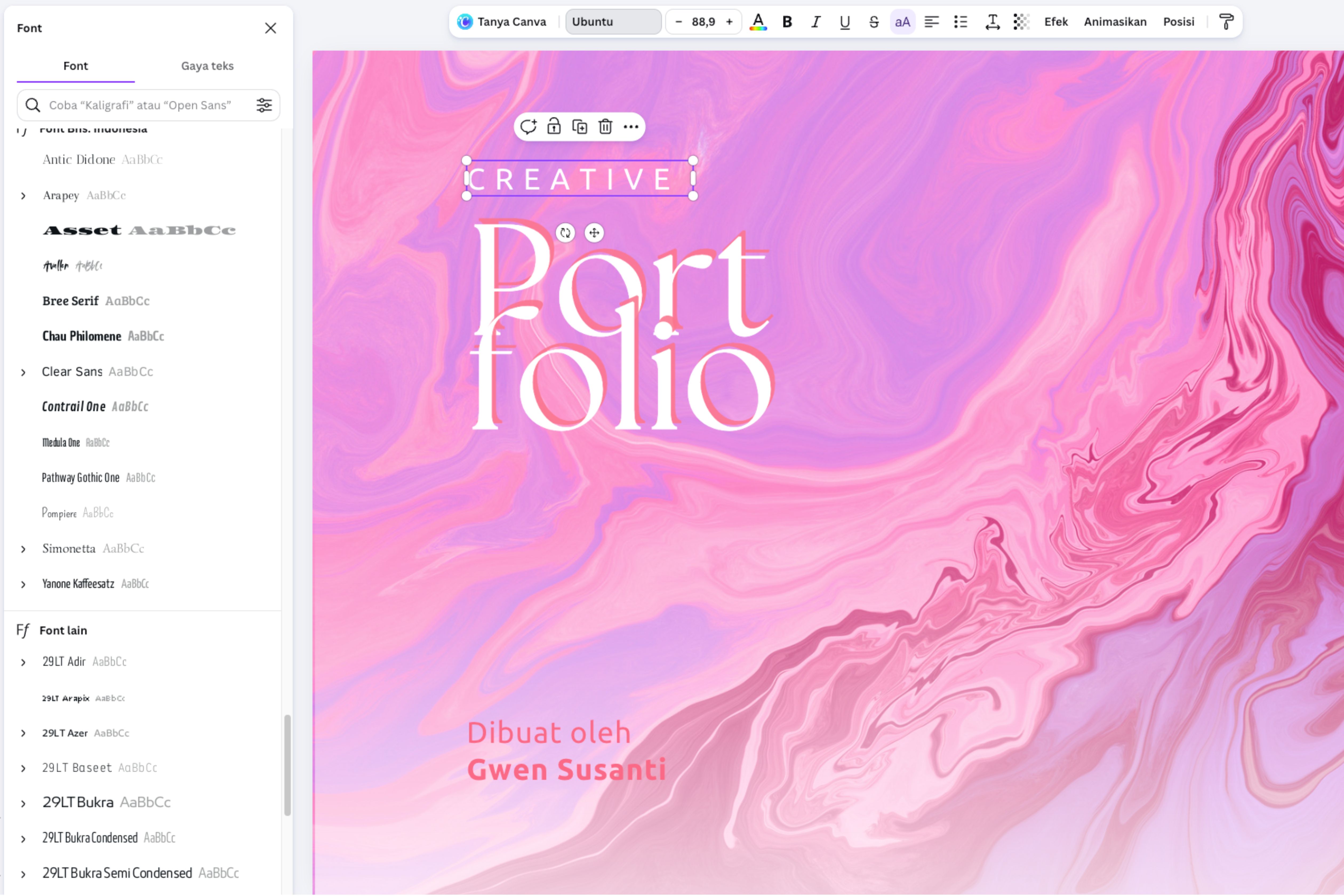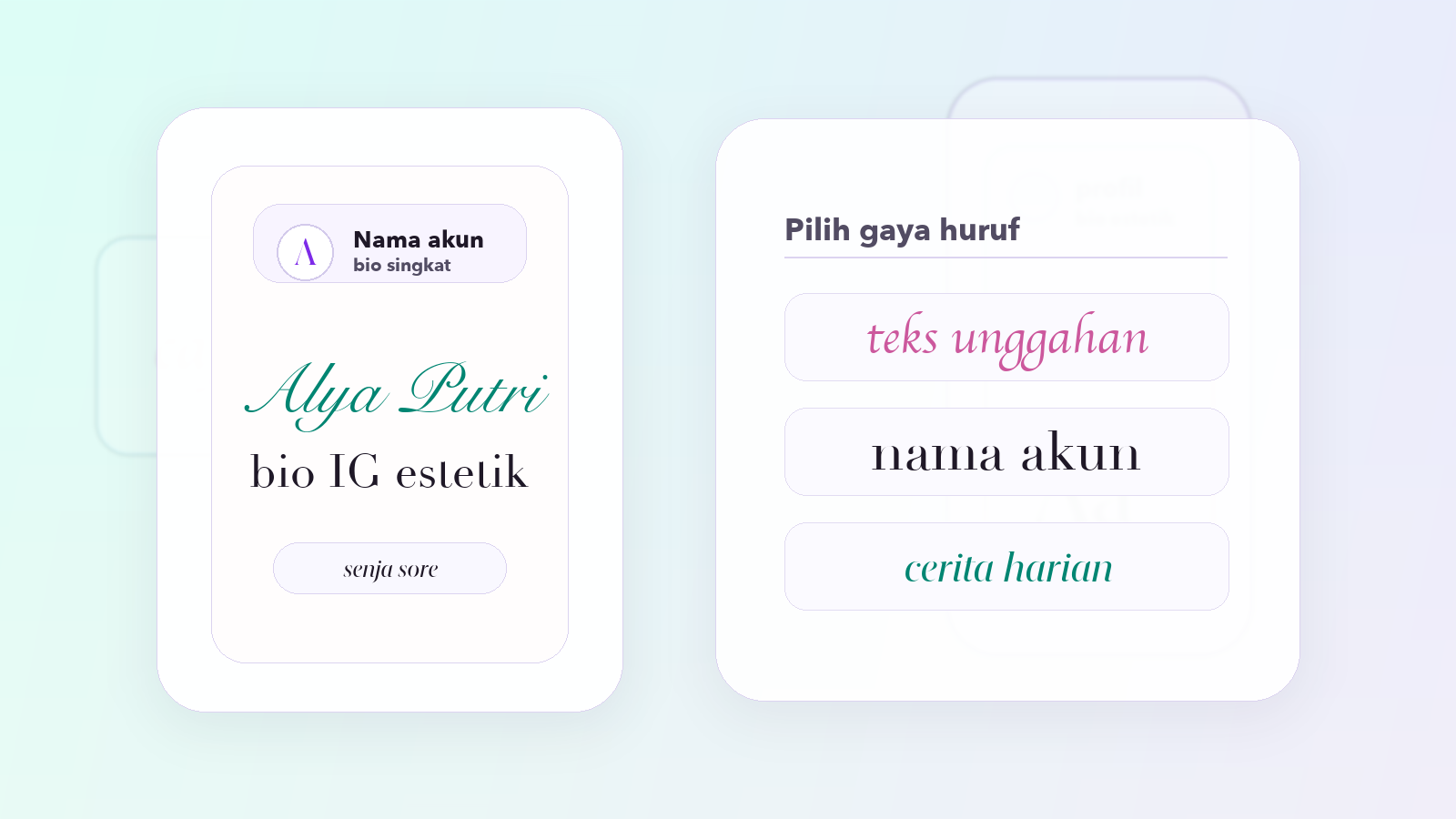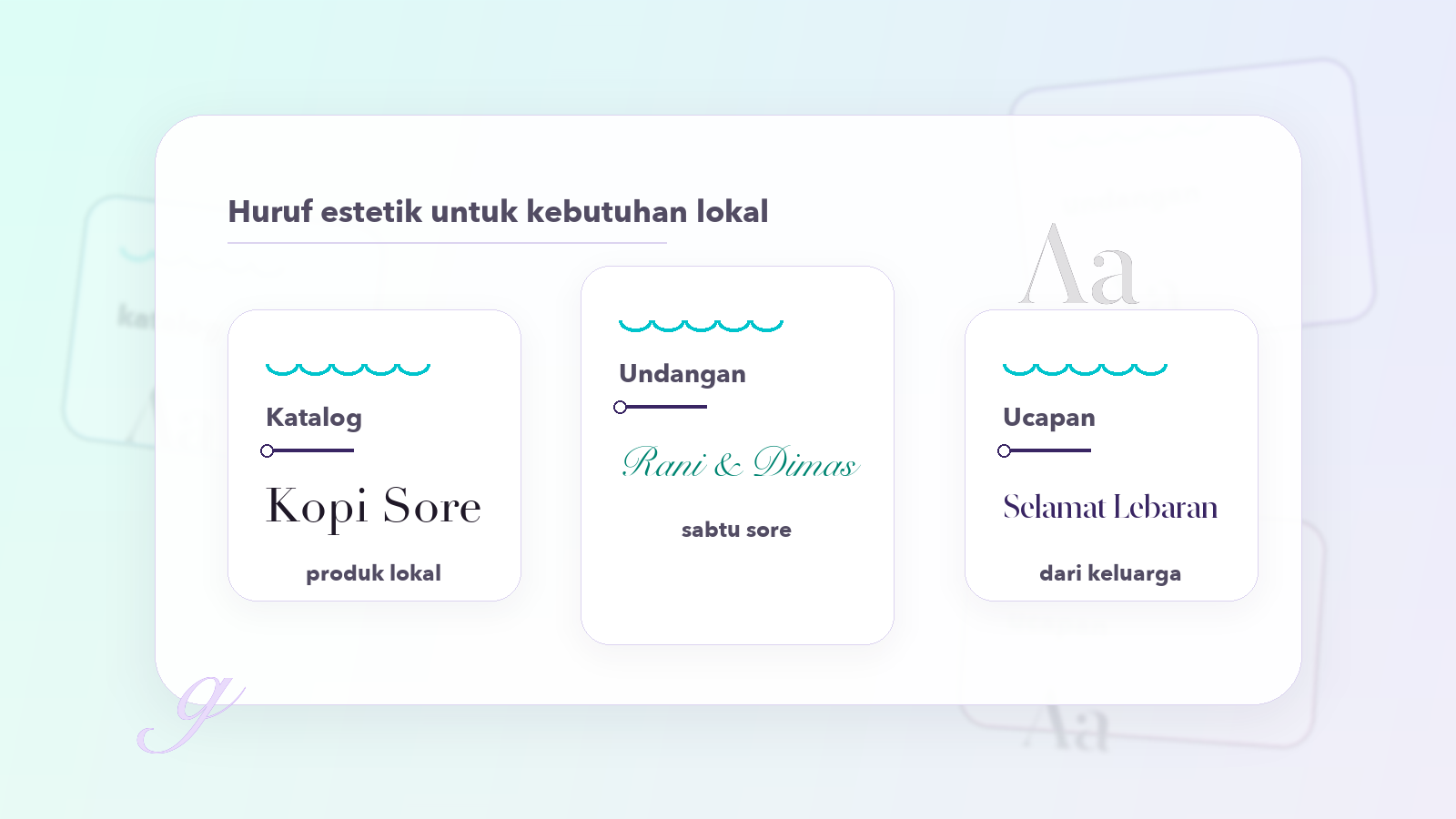
font aesthetic
Font aesthetic gratis untuk tulisan aesthetic
Pilih ratusan huruf aesthetic siap pakai di Canva untuk bio Instagram, nama akun, caption, dan judul. Ketik teks Anda, terapkan font aesthetic favorit, lalu unduh sebagai gambar, tanpa keahlian desain.
Ratusan huruf aesthetic gratis, langsung pakai
Canva menyimpan ratusan huruf aesthetic yang bisa Anda pakai gratis. Jenis font aesthetic-nya lengkap, mulai dari serif elegan, sans-serif modern, tulisan tangan, hingga display dekoratif.
Beberapa nama font aesthetic populer adalah Canva Sans yang bersih, Glacial Indifference yang minimalis, dan Playfair Display yang mewah. Cukup sorot teks, buka daftar font, lalu telusuri semua pilihan langsung di editor tanpa perlu mengunduh apa pun.
Perpaduan huruf aesthetic dan AI
Setelah teks dan visualnya siap, tinggal terapkan font pilihan Anda agar tampilan makin selaras. Perpaduan alat AI dan huruf estetik ini memangkas waktu dari ide sampai desain jadi.
Teks yang bisa diedit dan dipadukan
Berbeda dari gambar teks yang kaku, setiap font estetik di Canva menempel pada teks asli yang bisa Anda ubah kapan saja, termasuk lewat aplikasi Canva di iPhone dan Android.
Ganti kata, ukuran, warna, dan spasi hanya dengan beberapa klik, atau berganti font tanpa mengetik ulang. Untuk hasil terbaik, padukan satu font berkarakter untuk judul dengan satu font sederhana untuk isi, lalu simpan kombinasinya ke Kit Merek⁠(terbuka di tab atau jendela baru) agar konsisten di semua desain.
Font IG aesthetic untuk bio, caption, dan feed
Font Instagram aesthetic membuat bio, caption, dan feeds IG⁠(terbuka di tab atau jendela baru) terlihat menonjol. Pilih font IG aesthetic yang tipis atau bergaya tulisan tangan untuk kesan lembut, dan huruf tebal untuk judul agar mudah dibaca di layar ponsel.
Setelah desain siap, unduh sebagai gambar, unggah ke Instagram, atau bagikan lewat WA dan medsos lain. Cara ini lebih rapi dibanding menyalin tulisan aesthetic berbentuk unicode yang kadang gagal tampil di sebagian perangkat.
Untuk nama akun dan bio, coba font nama aesthetic yang tipis atau tulisan tangan agar profil terlihat rapi dan konsisten.
Huruf estetik untuk kebutuhan lokal
Di Indonesia, huruf estetik dipakai untuk banyak kebutuhan sehari-hari. Pelaku UMKM memakainya di feed jualan dan katalog produk⁠(terbuka di tab atau jendela baru) agar terlihat profesional, kreator konten menghiasnya di caption⁠(terbuka di tab atau jendela baru) dan thumbnail, sementara pelajar serta penggemar roleplay memilih gaya tertentu untuk bio dan nama akun⁠(terbuka di tab atau jendela baru).
Font estetik juga populer untuk undangan digital⁠(terbuka di tab atau jendela baru), ucapan, dan konten hari besar seperti Lebaran⁠(terbuka di tab atau jendela baru). Dengan koleksi font Canva yang aesthetic serta lengkap, Anda bisa menyesuaikan gaya dengan selera lokal maupun tren yang sedang ramai.
• Font aesthetic, atau aesthetic font, adalah huruf dengan gaya visual yang rapi, lembut, dan enak dipandang. Gaya ini banyak dipakai untuk bio Instagram, kutipan, nama, dan judul agar desain terlihat lebih estetik.
Pilih font yang mudah dibaca agar desain kaos kelas tetap keren saat dicetak.
• Ya. Canva menyediakan ratusan huruf estetik gratis yang bisa langsung Anda pakai di editor. Beberapa pilihan premium tersedia untuk akun berbayar, tetapi opsi gratisnya sudah sangat lengkap.
• Tambahkan kotak teks, ketik kata Anda, lalu pilih font aesthetic dari daftar font. Sesuaikan ukuran, warna, dan spasi huruf agar tulisan tampil rapi dan estetik.
• Jenis yang populer meliputi serif yang elegan, sans-serif yang modern, script atau tulisan tangan yang personal, dan display dekoratif untuk judul yang mencolok.
• Untuk Instagram, pilih gaya yang tipis atau bertekstur tulisan tangan pada bio dan caption, serta huruf tebal untuk judul feed agar mudah dibaca di layar ponsel.
• Buat teks di Canva memakai gaya pilihan Anda, lalu unduh sebagai gambar untuk Stories, highlight, atau status WhatsApp. Cara ini lebih rapi dibanding menyalin huruf unicode yang kadang gagal tampil.
• Bisa. Aplikasi Canva untuk Android dan iOS memuat daftar font yang sama dengan versi desktop, sehingga Anda dapat memilih gaya huruf langsung dari ponsel.
• Untuk judul poster, gunakan font display atau serif tebal yang berkarakter kuat agar terbaca dari jarak jauh. Padukan dengan sans-serif sederhana pada teks pendukung.
• Tambahkan kotak teks, ketik nama Anda, lalu pilih font aesthetic bergaya script atau serif tipis. Atur ukuran dan spasi huruf agar nama tampil rapi untuk bio, feed, atau kartu nama.